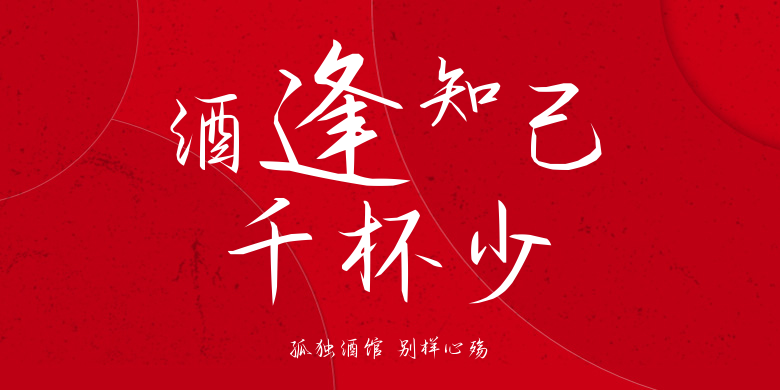
孤独酒馆 别样心殇
孤独酒馆 别样心殇,这款字体结构工整、笔画清晰,兼顾美观与易读性,适用于标题、正文、海报、包装、LOGO 等多种场景。字形优雅稳定,风格百搭耐看,适配日常排版与创意设计,让文字呈现更舒适、更具质感。孤独酒馆 别样心殇一笔一画,皆是细节,以均衡的比例、流畅的线条打造舒适视觉体验,字形端正大气,风格简约现代。无论是商业设计、品牌宣传还是日常排版,都能轻松驾驭,让文字更有格调与力量。孤独酒馆 别样心殇字体下载。